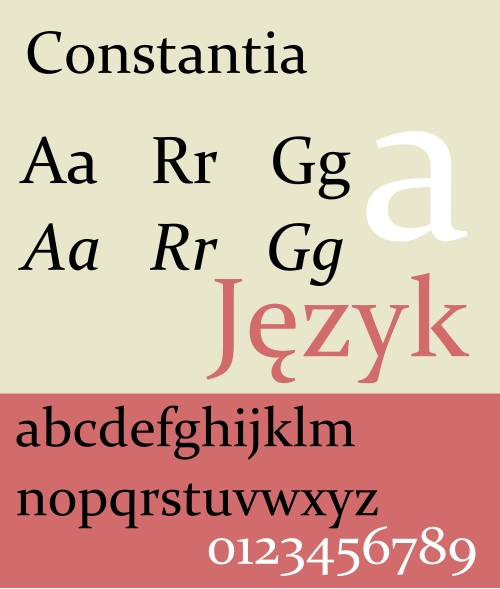
| カテゴリ | セリフ |
| 分類 | 移行期 |
| デザイナー | ジョン・ハドソン[1] |
| 鋳造所 | マイクロソフト |
コンスタンティアは、ジョン・ハドソンがマイクロソフトの依頼でデザインしたセリフ 書体です。 [2]エリック・ギルのペルペチュアデザインの影響を受けた過渡期のセリフデザインです。この書体の開発は2003年に始まり、2004年にリリースされました。
Constantia は、 Windows Vistaでリリースされたさまざまなデザイナーによるフォント スイートであるClearType フォント コレクションの一部です。すべてのフォントの先頭文字がCで始まるのは、Microsoft のClearTypeテキスト レンダリング システム (LCD モニターでテキストを明瞭に読み取れるように設計されたテキスト レンダリング エンジン)で適切に動作するように設計されていることを示しています。スイートに含まれる他のフォントは、Calibri、Cambria、Candara、Consolas、Corbelです。
特徴
Constantiaは印刷と画面上のどちらでも使用できるようにデザインされた。サンプル画像に見られるように、数字はデフォルトでテキスト数字である。このフォントには代替スタイルとしてライニング数字も含まれている。ウェブサイトTypographicaでこのフォントをレビューしたRaph Levienは、「このフォントスイートの中では誰もが一番好きな書体になるだろう...非常に読みやすいローマンフォントで、古典的なモデルからわずかに逸脱しているが、それでも新鮮で新しい。Perpetuaからインスピレーションを得ている...しかし三角形のセリフは彫刻刀を思い起こさせ、このフォントにはPalatinoを思い起こさせるほどのカリグラフィの風味がある」と評した。[3]他の機能としては、このデザインにはスモールキャップ、大文字テキスト用の代替スペースと句読点、円で囲まれた数字、上付き文字と下付き文字のグリフなどがある。
トランジショナル セリフデザインは、太いストロークと細いストロークの適度なコントラストとほぼ垂直の軸が特徴です。ClearType で適切にレンダリングするために、文字OとQは少し角張っています。
ハドソンは、その名前について次のように説明しています。「思いついた名前の候補を全部思い出すことはできません。どれも国際的な商標検索で却下されました...夕べの祈りの間に賛美歌を歌っていたとき、constantiaという単語に気づきました。ああ、これは C で始まるんだ!」[8]ハドソンは、2011年の執筆で、「実は Constantia という名前はあまり好きではなく、フェリーを待っている間に埠頭で海鳥を見るたびに、Cormorantと名付ければよかったと思うのです。」とコメントしています。 [9]